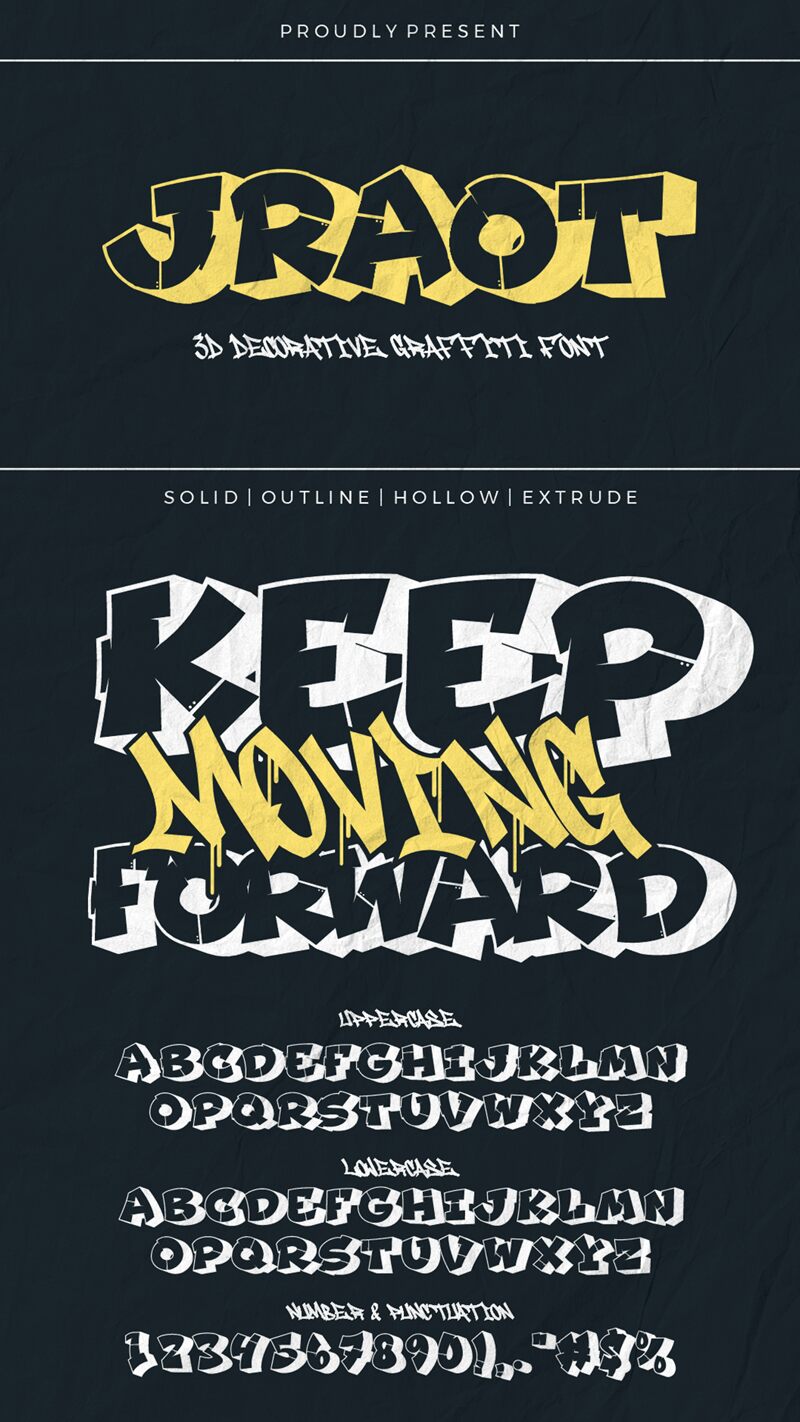
Jraot Outline od Sipanji x Cikareotype je bezplatné komiksové písmo typu display, definované velkými siluetami připomínajícími papírové výstřižky, které se mezi písmeny naklánějí, vlní a nafukují. Obrysové tvary si zachovávají živý švih, zatímco vnitřní linie dodávají písmenům dojem, jako by byla vyrobena ze složeného kartonu, a ne jen vykreslena jako přesný geometrický vzor.
Tato netradiční hmota dodává krátkým titulkům sílu na plakátech pro děti, obálkách komiksů, miniaturách pro YouTube, letácích či hravých obalech. Písmo se také skvěle hodí na samolepky a merchandising, kde silný obrys a nepravidelný kreslený rytmus fungují jako výrazný grafický prvek i bez potřeby dalších dekorací.